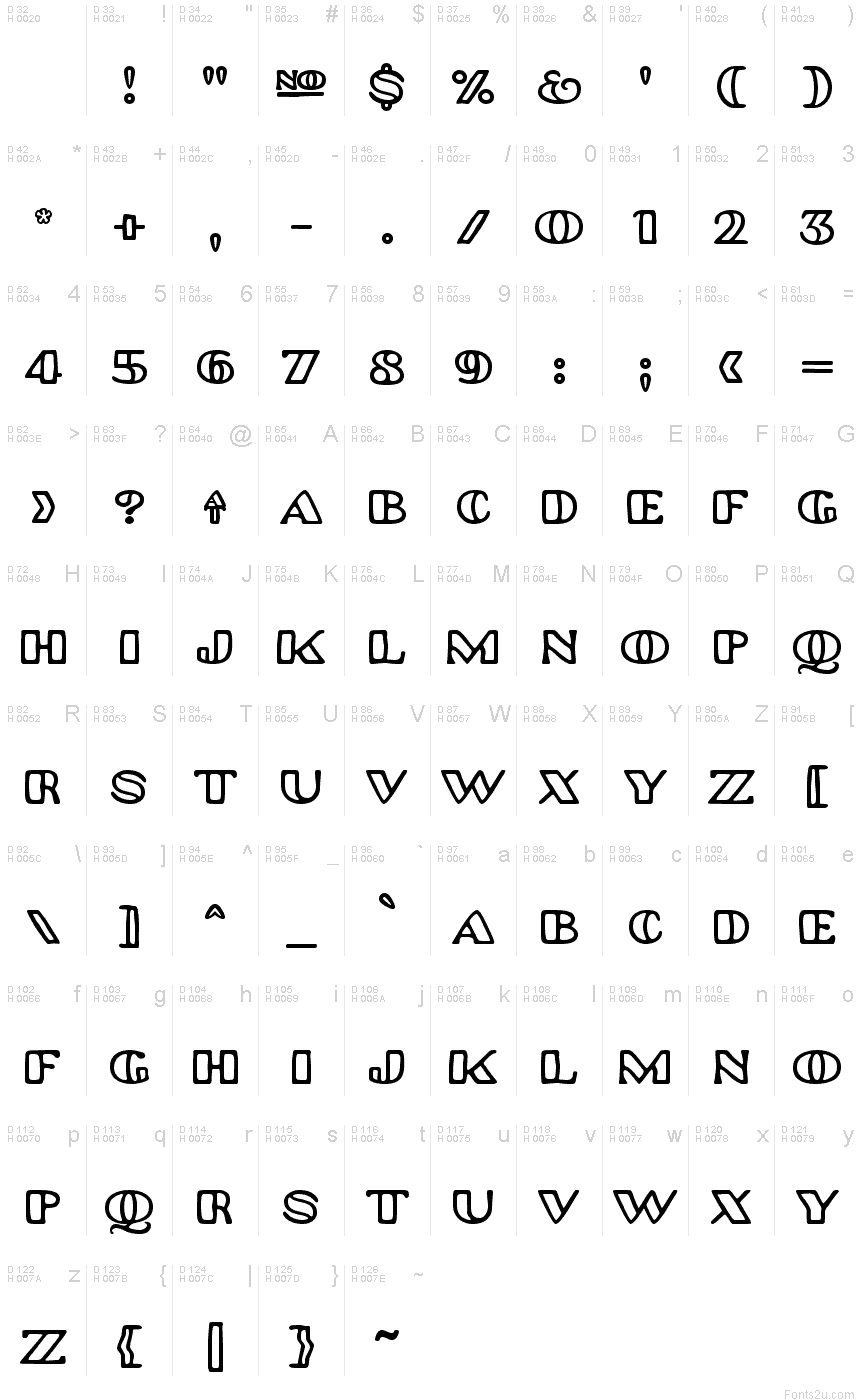
Platinum Hub Caps
Platinum Hub Caps, autorstwa R.Gasta z GreyWolf WebWorks, to darmowy, konturowy font display w stylu retro-futurystycznym, który wyróżnia się masywnym charakterem, inspirowanym napisami na autach customowych i grafiką techno z końca XX wieku. Litery są szerokie, delikatnie kanciaste i obrysowane grubą linią, co nadaje krojowi gładki, napompowany wygląd, przypominający chromowane kołpaki i tytuły gier arcade.
Sprawdza się na plakatach, logach gier, okładkach zinów, klubowych ulotkach i planszach tytułowych, gdzie krótki tekst potrzebuje zaokrąglonego, mechanicznego blasku. Jako darmowy font, świetnie nadaje się również do monogramów, inicjałów i oznaczeń na opakowaniach, ponieważ wyrazisty kontur nadaje nawet krótkim słowom stylizowany, przypominający odznakę charakter.